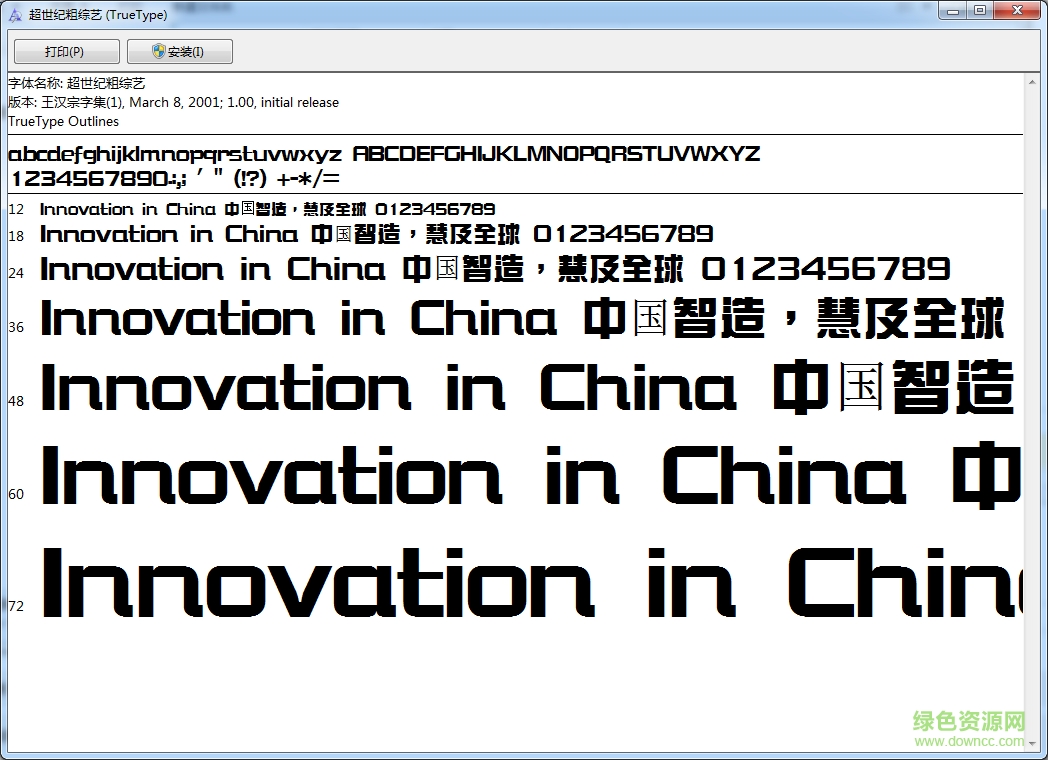
超世纪粗综艺
超世纪粗综艺是一款独具特色的是超世纪字体软件,字体简洁美观大方,字体在很多领域应用都特别的广泛,使用非常便捷。有需要使用这款字体的朋友快来绿色资源网下载体验吧!
超世纪粗综艺是超世纪字体库中的一种字体,字体威武有形,力道十足,可应用于绘画设计、杂志报刊、平面广告、印刷包装等领域,喜欢的朋友可免费下载收藏。